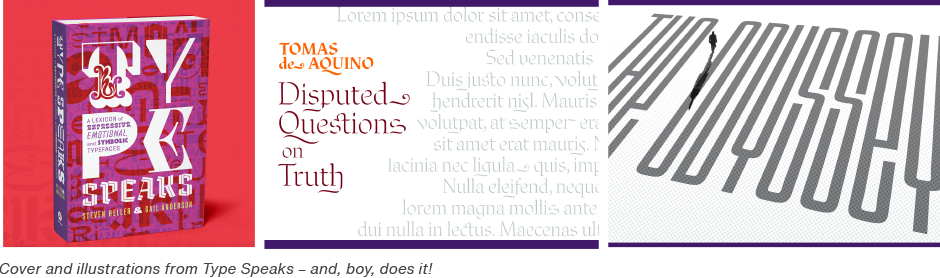
Tendances par type : 2022 Tendances T2 par Gail et Joe
Gail Anderson
Un duo dynamique parle de la typographie
Marvel Comics a Black Widow et Daredevil. Les amateurs de crème glacée ont Ben et Jerry. Les cinéphiles ont Thelma et Louise. Et les typophiles ? Ils ont Gail Anderson et Joe Newton.
Rencontre avec Gail et Joe
Nous avons récemment rencontré Gail Anderson et Joe Newton, de AND (Anderson Newton Design), pour discuter de l'un de leurs sujets de prédilection : la conception typographique. Gail et Joe ont lancé le studio, début 2012, en tant qu'agence dédiée à un design sophistiqué mais plein d'esprit - avec un accent particulier sur la typographie. Un accent qui, soit dit en passant, est aiguisé comme un laser et délicieusement ludique.
De 2002 à 2010, Gail a occupé le poste de directrice de la création chez SpotCo, une agence de publicité de New York qui crée des œuvres d'art pour Broadway et le théâtre institutionnel. Auparavant, elle a travaillé pour le magazine Rolling Stone, dont elle a été la directrice artistique principale. Elle a écrit pour des livres, des magazines et des blogs, et donne des conférences dans le monde entier sur tout ce qui touche au design.
Gail est actuellement présidente des départements BFA Design et BFA Advertising de la School of Visual Arts (SVA). Elle est également directrice créative de Visual Arts Press, le studio de création interne de l'école. Son travail a été reconnu par des organisations de design telles que The Society of Publication Designers, TDC, AIGA, The Art Directors Club, Graphis, HOW, Print et Communication Arts.
Oh, et Gail crée également des dessins typographiques qui vous font tomber à la renverse.
Joe a travaillé des deux côtés de la table. En tant que directeur artistique, il a créé un nombre incalculable de couvertures et de reportages, et a réalisé des centaines d'illustrations et de photos pour Rolling Stone et The Stranger de Seattle. Chez Veer, Joe était responsable de l'identité visuelle et du contenu de la division Polices . Sa conception typographique ressemble à l'odeur du bacon.
En tant qu'illustrateur, Joe a travaillé avec des publications telles que le New York Times, Vibe et le magazine Nickelodeon, et pour des clients tels que Sony Music et Publicis. Ses œuvres ont été récompensées par American Illustration, Communications Arts et Print. Sa conception a été reconnue par le Print Magazine, la Society of Publication Designers et la Society of Illustrator.
Il s'agit de nouveauté, de voix et d'énergie
Gail et Joe forment une équipe. Ils travaillent ensemble - en étroite collaboration - et se complètent mutuellement. Cela ne signifie pas pour autant qu'ils ont un seul et même esprit lorsqu'il s'agit d'élaborer un design typographique de qualité.
Vous voulez en savoir plus sur la façon dont ce duo dynamique travaille ensemble et sur ce qui motive leur conception ? "Écoutez notre conversation ci-dessous.
Les solutions typographiques d'AND sont très illustratives et évocatrices. Quelle est l'idée sous-jacente ?
Joe Newton (JN) : J'ai commencé ma carrière en tant qu'illustrateur. Je considère la typographie comme un élément physique de la composition, un mot-image. Elle ne doit jamais être simplement superposée à un dessin. Les caractères peuvent avoir une présence expressive et physique. Je pense que Gail traite les caractères de la même manière. Nous avons toutes deux une formation en conception éditoriale. J'ai travaillé pour la première fois pour un hebdomadaire d'information qui disposait d'un budget artistique minime. La typographie offrait un moyen de créer une attitude et de l'énergie.
Qu'est-ce qui motive vos choix personnels en matière de polices de caractères et de conception typographique ?
Gail Anderson (GA) : Je suis facilement séduite par les solutions ludiques et les caractères vernaculaires. Mais les classiques restent époustouflants, intemporels et, en fin de compte, irrésistibles. Je n'ai pas l'impression d'avoir la main assez légère ou de savoir quand m'arrêter, alors il est plus facile de travailler avec des choses plus sottes.
JN : Oooh, ce qu'elle a dit ! Trop n'est jamais assez. J'ai passé une demi-douzaine d'années en tant que responsable des caractères pour Veer.com (qui distribuait polices et des images de stock). Je devais trouver un moyen de convaincre les clients que chaque caractère était unique et méritait leur argent. J'ai donc créé des spécimens pour chaque version. Aujourd'hui encore, chaque fois que je vois une nouvelle police de caractères que j'aime, j'ai envie de la mettre en œuvre. Je veux une nouvelle police de caractères pour chaque projet.
Quels conseils donneriez-vous pour le choix des polices de caractères ?
GA : Le monde de la typographie est extraordinaire - bien plus que ce qui est fourni avec votre ordinateur. Faites une recherche approfondie sur MyFonts.com, achetez de vieux livres de caractères et constituez votre collection personnelle de favoris.
Lorsque vous cherchez la police de caractères appropriée, essayez de ne pas vous laisser aller à taper "chocolat" dans la barre de recherche, alors que vous êtes en train de mettre en valeur une barre de chocolat. C'est trop facile. Trop évident. Et presque jamais juste.
Les derniers mots de Joe
Je pense qu'il y a actuellement une réaction à la tendance de la dernière décennie en matière d'image de marque, qui a tout réduit à une police de caractères universellement inoffensive. Aujourd'hui, les gens essaient de donner des voix plus particulières aux caractères, de rendre les marques plus humaines et la communication plus vivante.